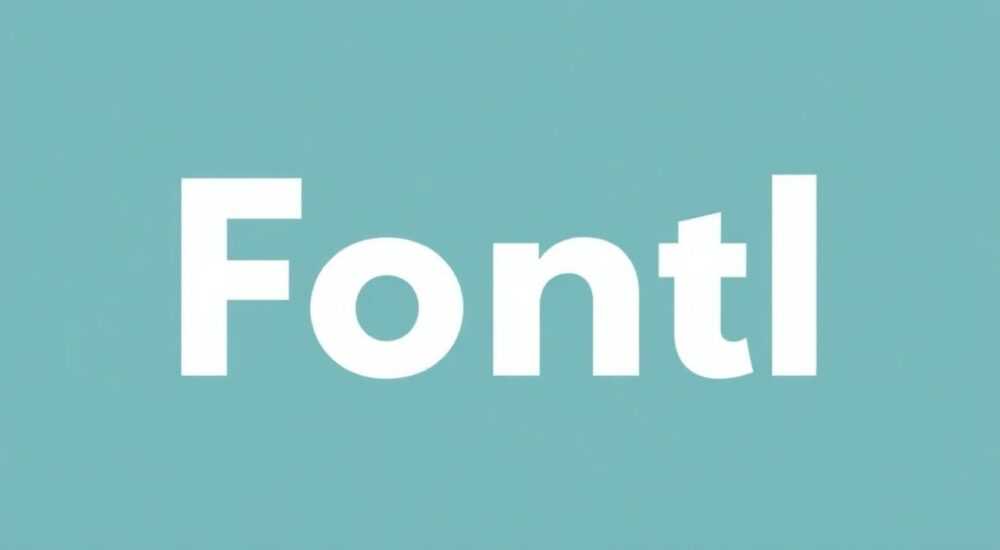
Как использовать шрифты в фигме
В современном цифровом дизайне шрифты — не просто набор символов, а ключевой элемент бренда, удобства и эмоционального восприятия интерфейса. В Figma, где дизайн превращается в прототипы, а коллаборации происходят в реальном времени, правильное использование шрифтов влияет на скорость работы команды, согласованность продукта и даже конверсию. Неправильно подобранный шрифт может разрушить всю визуальную иерархию, а отсутствие систематизации приводит к хаосу в дизайнерских файлах. Именно поэтому понимание, как управлять шрифтами в Figma — не опциональный навык, а базовая компетенция каждого дизайнера.
Почему шрифты — это не просто текст
Шрифты формируют первое впечатление о продукте. Исследования Nielsen Norman Group показывают, что 67% пользователей оценивают надёжность сайта на основе читаемости текста. Если текст трудно воспринимать — пользователь уходит. В Figma это особенно критично, потому что дизайн-системы, созданные без чёткой типографики, превращаются в «сборище текстовых блоков», где каждый дизайнер использует свои настройки: размер, межстрочный интервал, выравнивание. Результат — несогласованность между экранами, отсутствие масштабируемости и рост времени на ревью.
Представьте: вы проектируете мобильное приложение для банка. Заголовок «Ваш баланс» должен быть чётким, уверенным, легко читаемым даже в движении. А подпись «Транзакция выполнена» — спокойной, дружелюбной. Разница не в содержании, а в шрифте. Именно поэтому шрифты — это инструмент коммуникации, а не декор.
Как создавать и управлять стилями шрифтов в Figma
Figma позволяет создавать глобальные стили шрифтов — это основа любой профессиональной дизайн-системы. Чтобы начать, перейдите во вкладку «Styles» в левой панели и нажмите «+» рядом с «Text Styles». Здесь вы создаёте шаблон, который можно применять ко всем текстовым слоям.
Для каждого стиля задайте:
— Шрифт (семейство)
— Размер
— Вес (light, regular, medium, bold и т.д.)
— Межстрочный интервал (line height)
— Интервал между символами (letter spacing)
— Выравнивание (left, center, right, justify)
Чтобы применить стиль, выделите текстовый слой, откройте панель свойств справа и выберите нужный стиль из выпадающего меню. Если стиля нет — создайте его прямо отсюда, нажав на иконку «Создать стиль».
Шрифтовые семьи и варианты: как не запутаться
Современные шрифты — это не один файл, а целые семьи с десятками вариантов: Thin, Light, Regular, Medium, SemiBold, Bold, ExtraBold, Black. Figma позволяет работать со всеми вариантами в одном семействе, но только если шрифт установлен как системный или загружен через Figma’s font library.
Частая ошибка: дизайнер выбирает «Roboto Bold» для заголовка, а потом для подзаголовка — «Roboto Medium». Это работает, пока не придётся менять шрифт на «Inter». Тогда нужно вручную перебирать сотни слоёв. Решение — использовать шрифтовые стили, а не отдельные варианты.
Правильный подход:
1. Создайте стиль «H1» → шрифт: Roboto, вес: Bold, размер: 32px.
2. Создайте стиль «H2» → шрифт: Roboto, вес: SemiBold, размер: 24px.
3. При смене шрифта на Inter — просто измените шрифт в стиле H1 и H2. Все тексты обновятся.
Функция |
Рекомендуется |
Избегать |
Название стиля |
H1-Primary, Body-Large-Secondary |
Text 1, Title, Bold Text |
Вес шрифта |
Использовать встроенные веса (Regular, Bold) |
Ручная настройка веса через «Font Weight» |
Межстрочный интервал |
1.2–1.5 от размера шрифта |
Фиксированные значения в px без привязки к размеру |
Создание типографической системы: шаг за шагом
Типографическая система — это набор правил, определяющих, как текст должен выглядеть в любом контексте. Она включает: размеры, веса, интервалы, цвета и правила применения. Вот как создать её в Figma:
- Определите иерархию: заголовки (H1–H6), подзаголовки, основной текст, подписи, кнопки, метки. Каждый уровень должен отличаться по весу и размеру.
- Выберите 2–3 шрифтовых семьи: один для заголовков (например, Inter Bold), один для основного текста (Inter Regular), возможно — третий для акцентов (например, Poppins для кнопок).
- Создайте стили для каждого уровня: не менее 8–12 стилей для полноценной системы. Не забудьте про инлайновые стили: «Link», «Caption», «Badge».
- Настройте межстрочные интервалы: используйте относительные значения (например, 1.4 для Body, 1.2 для H1). Это гарантирует пропорциональность на разных экранах.
- Сохраните систему как шаблон: экспортируйте файл с типографикой как «Design System Template» и делитесь им с командой через Figma Community или командную библиотеку.